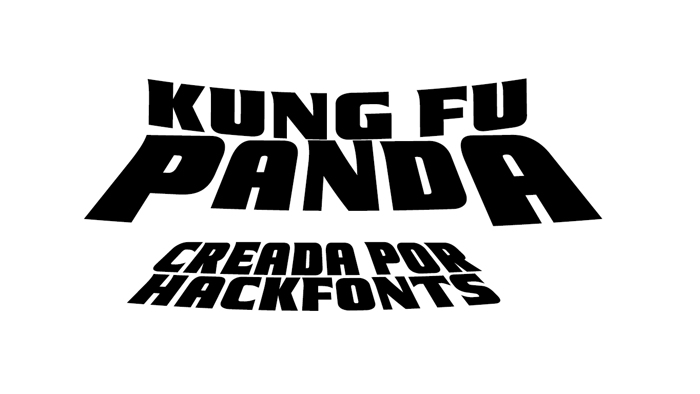
Kung Fu Panda Font
TIPOGRAFÍA DE LA PELÍCULA 'KUNG FU PANDA' KUNG FU PANDA 2' KUNG FU PANDA 3 Y TAMBIÉN SEGUIDO DE SUS JUEGOS OFICIALES VIA ANDROID Y/O PC